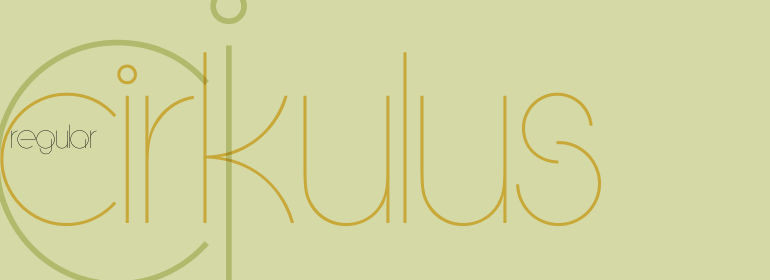
Cirkulus™
Cirkulus是一种实验性显示字体,有极细线的圆形和直线构成。该字体是Michael Neugebauer于1970年设计的。这些字母散发出一种建构主义气息,让人联想起20世纪20年代的革命和90年代的数字实验。Cirkulus是一款具有非常纤细外观的单盒字母,应该只能使用大型显示尺寸。
Cirkulus is an experimental display face, constructed using combinations of hairline circles and straight lines. The typeface was designed by Michael Neugebauer in 1970. The letters exude a constructivist aura, reminiscent of both the revolutionary 1920s, and the digital experiments of the 1990s. Cirkulus is a unicase alphabet, with a very lightweight appearance, and should be used solely in large display sizes.